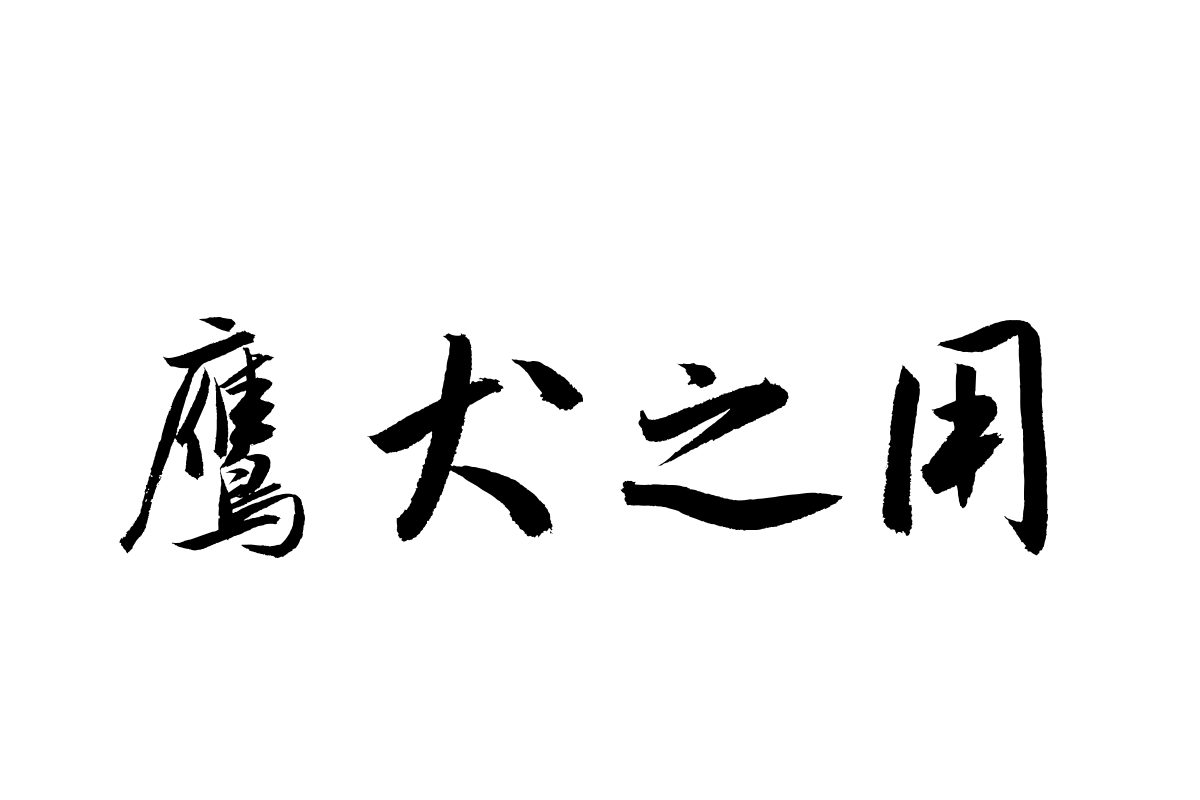
汉仪孟嘉伟行书繁体是一套由汉仪公司推出的中文字体,主要用于书法、美术和设计等领域。这套字体的特点是笔画流畅、结构紧凑,具有很高的艺术性和实用性。
汉仪孟嘉伟行书繁体的特点如下:
1. 笔画流畅:这套字体的笔画线条平滑,没有过多的断线和毛刺,给人一种流畅的感觉。
2. 结构紧凑:虽然笔画流畅,但每个笔画都保持了一定的空间,使得整个字体看起来更加紧凑有序。
3. 艺术性强:这套字体的设计注重艺术性,每个字都有独特的风格和韵味,适合用于书法、美术和设计等领域。
4. 实用性高:这套字体适用于多种应用场景,如印刷、电子屏幕显示等,具有较高的实用价值。
总之,汉仪孟嘉伟行书繁体是一款具有很高艺术性和实用性的中文字体,适用于各种设计和创作领域。